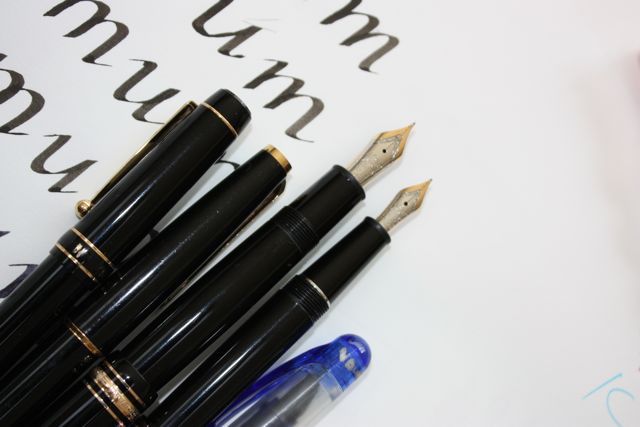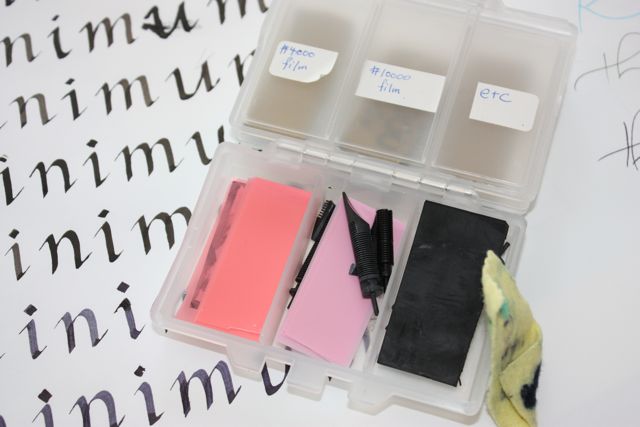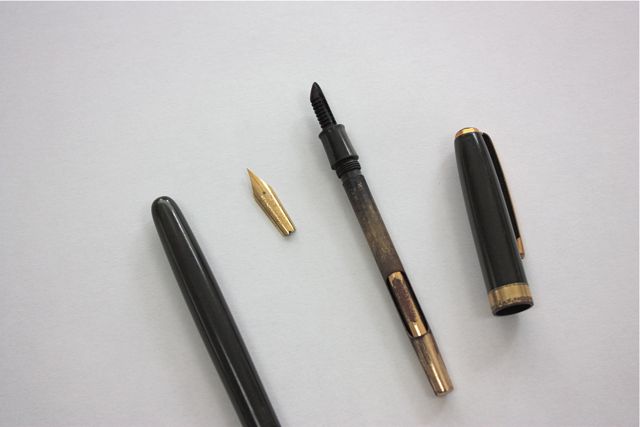
万年筆愛好家来訪
先週は、ギャラリ―羽ペン工房で、J-LAF主催の展覧会が開催されていました。
そこへ、高校生のkouki君登場。万年筆愛好家の来訪です。
ちょうどこの日はクラスがあったので、レッスンに飛び入り参加してもらって、文字を書いてもらいました。文房具や書く道具に興味があるだけあって、スイスイどんどん書いて行くので、まわりの生徒さんたちも驚きです。画像は彼の練習したものです。
ちゃんと万年筆数本と修理セット?を持って来られていて、いろいろと見せてくださいました。
高そうな(実際とても高価なものです)モンブランや100円ショップで買って自分で調整したものなど、そのこだわり心が伝わる物ばかり。
以前このブログでもご紹介しましたが、祖父からもらった古い万年筆があったので、それを見てもらいました。簡単に分解してくれました。ペン先の金の部分だけになるなんて、びっくり!
いろいろとお掃除してくれた結果、書ける様になりました。祖父の感じた書き味をもういちど確かめることが出来て本当に感動です。
それにしても、高校2年生でこんなに詳しいなんて!今から大好きで夢中になれるものに出会えているなんて、本当にすばらしい!
嬉しいことに、kouki君の調整してくれた万年筆をお土産に頂きました。
ちゃんと太い線と細い線が書ける様にしてくれています。カリグラフィー用にしてくれたんですね。ありがとう。
普段から万年筆で書いてみようと思います。
万年筆愛好家のkouki君、高校生なんですね。以前に美しい文字を描きたいと書かれていた記憶があります。ちょっと古いのですが、Write Now: The Complete Program For Better Handwriting by Barbara Getty and Inga Dubayという独学用のハンドライティングの本は、ちょうど万年筆でアルファベットの練習が出来るようになっています。ちょっと。おすすめです。
Barbara Getty and Inga Dubayの本は、Italic Letters-Calligraphy & Handwritingという本なら持っています。Revised editionとなっているので、もしかしたら同じものかしら。文章もすべて手書きの本です。
以前日本ではぬり絵が流行ったことがありましたが、こういうなぞり書きができる練習帳も、きっとやってみたらハマりそうですね。実際、奥の細道を鉛筆でなぞり書き!なんていう本も出ていますよね。